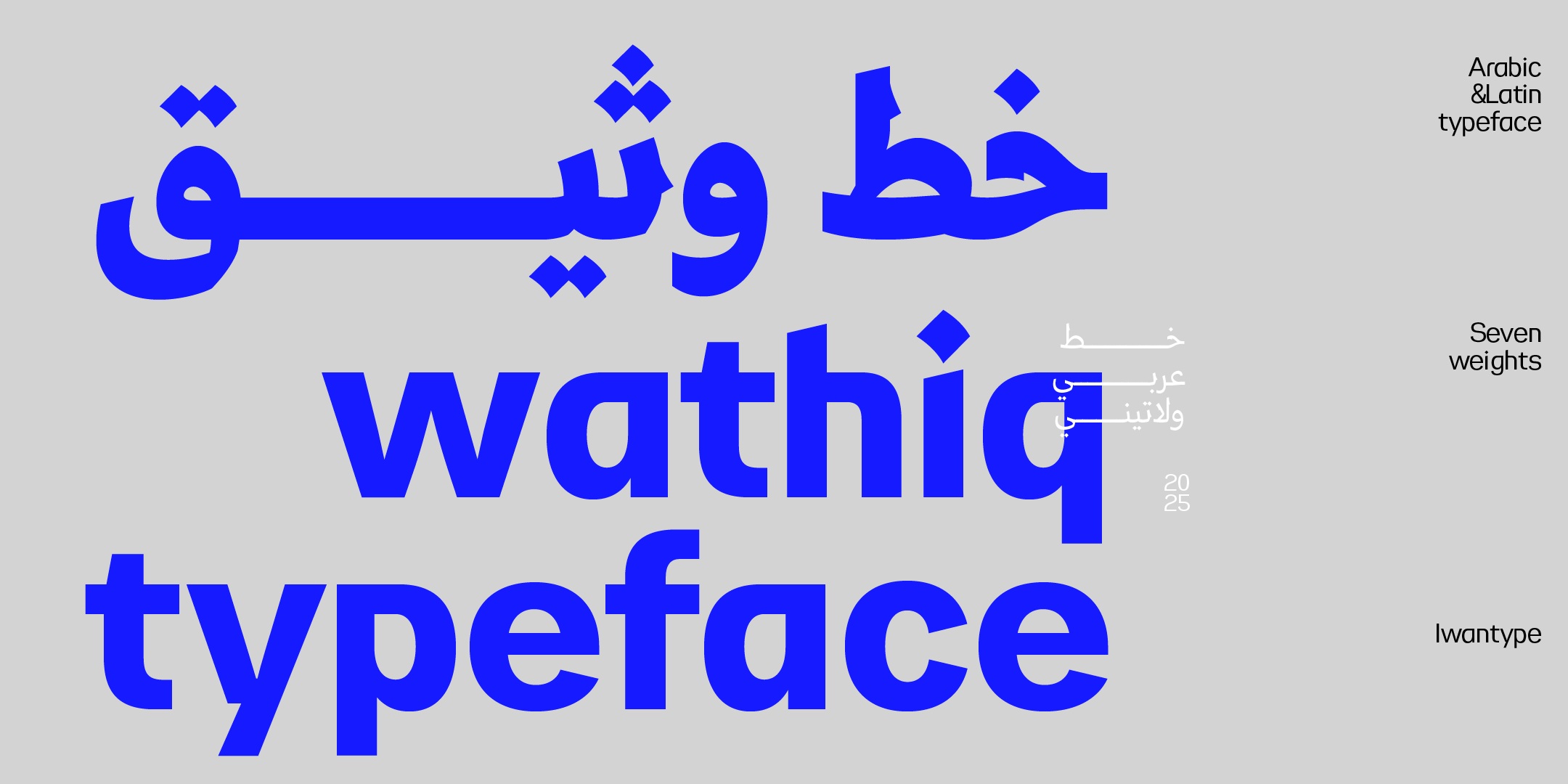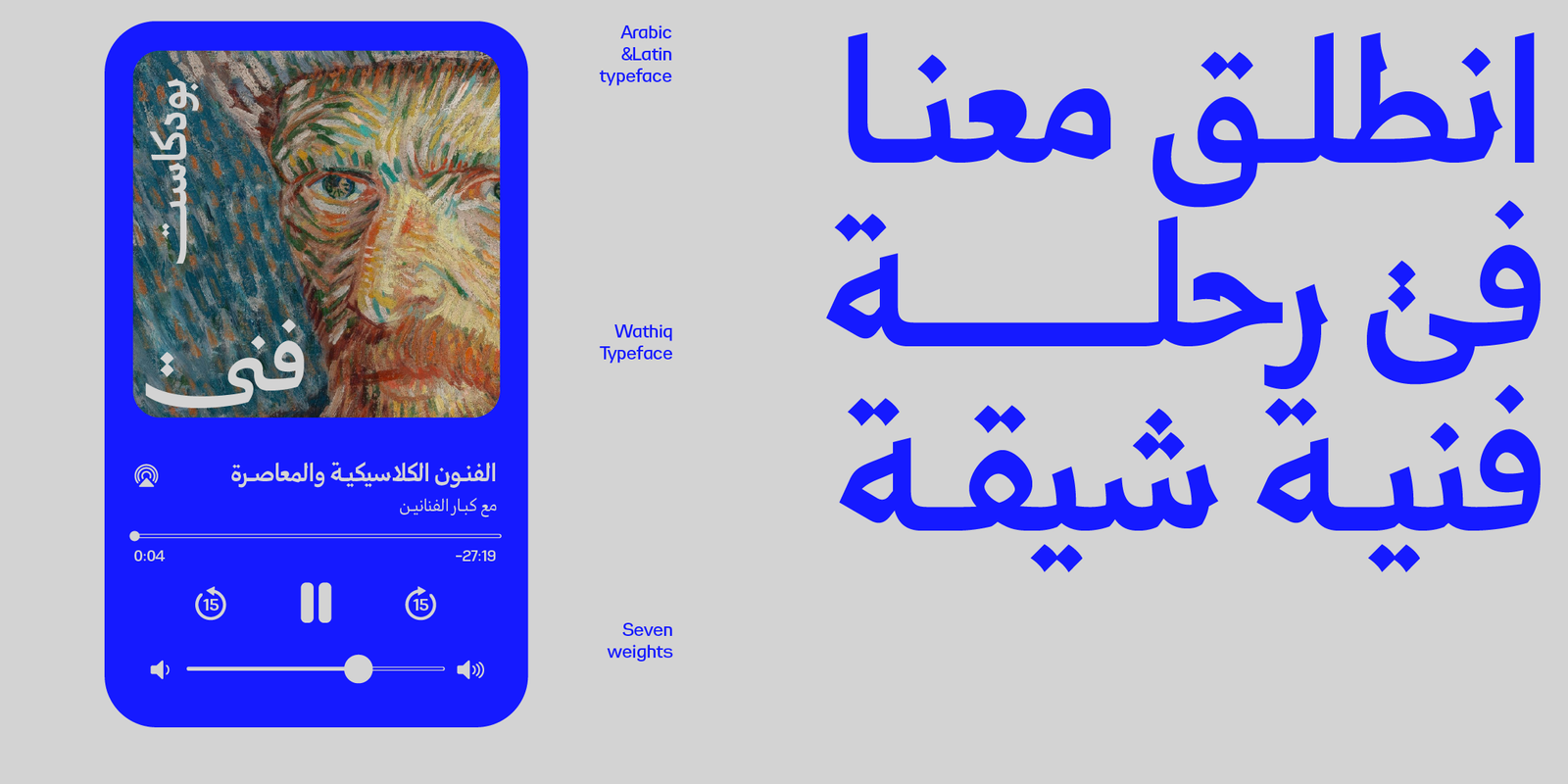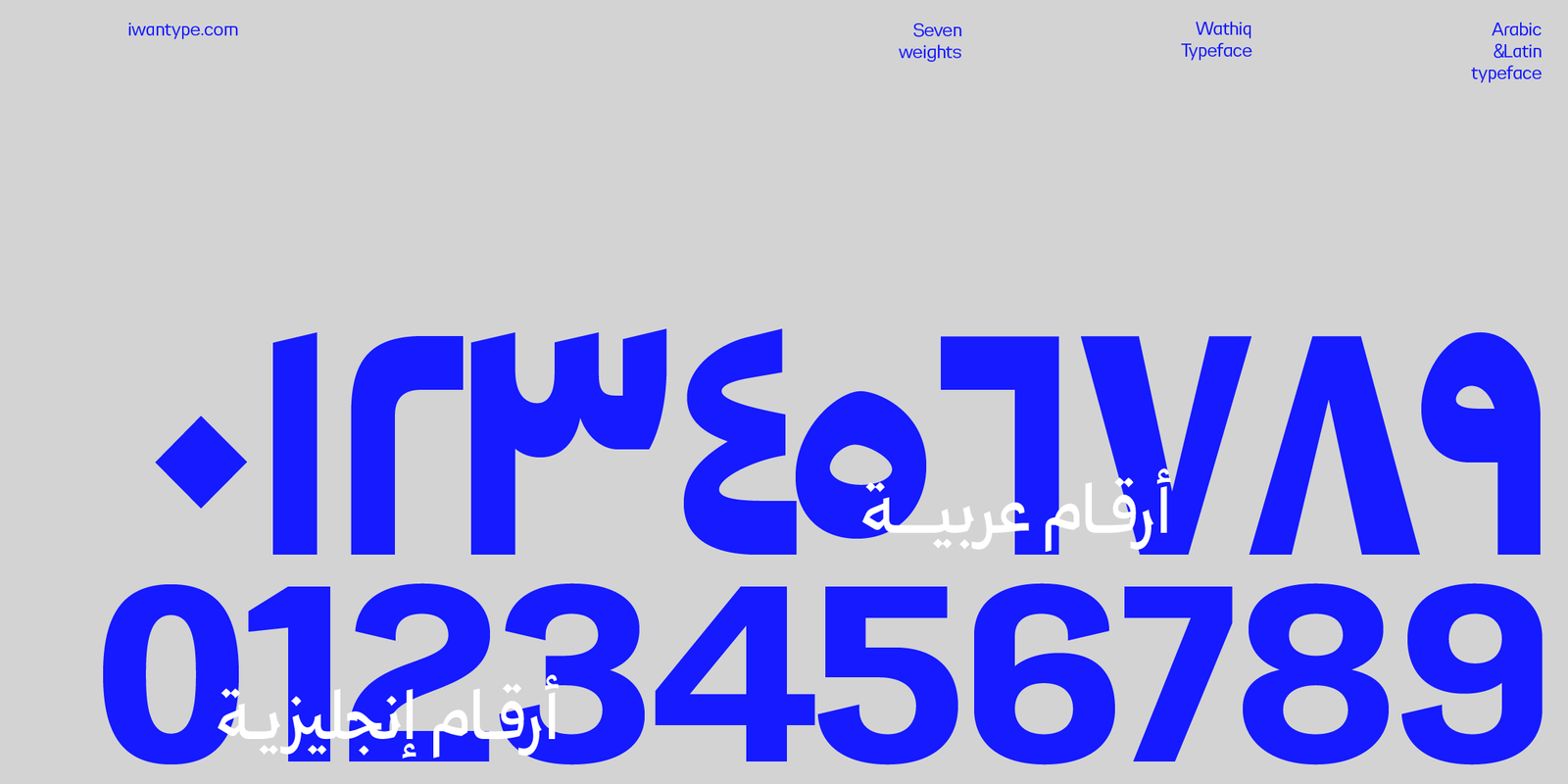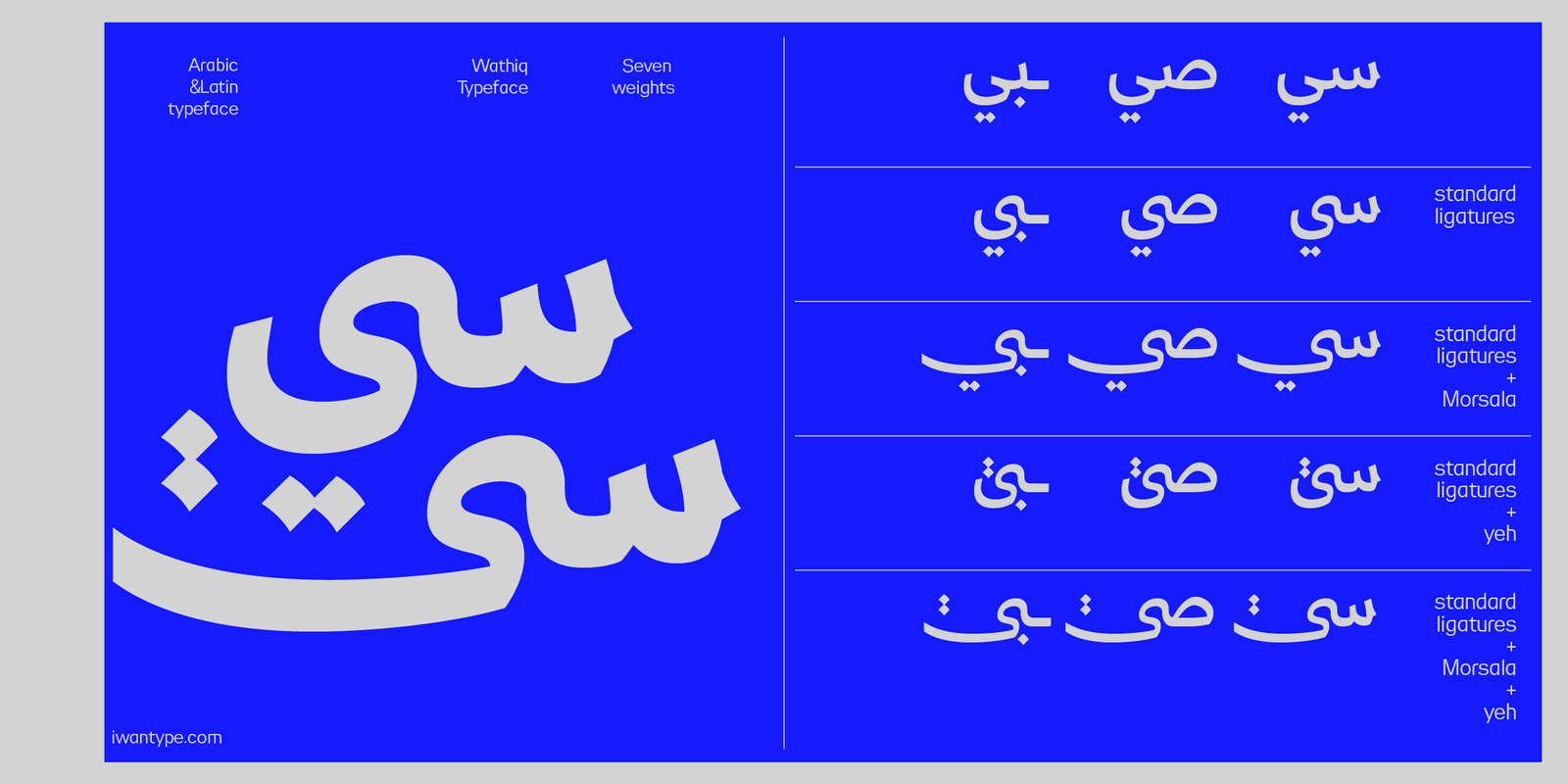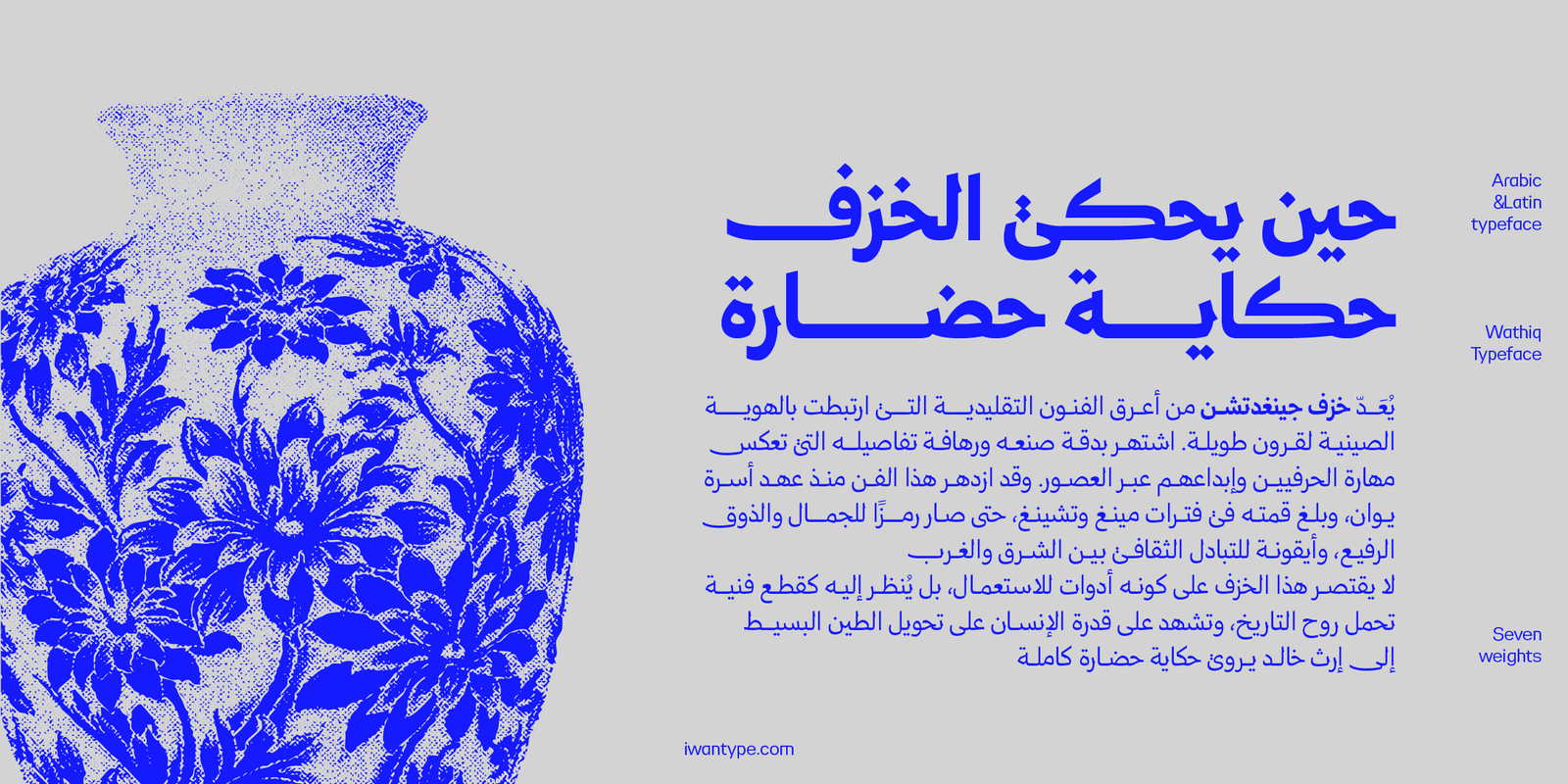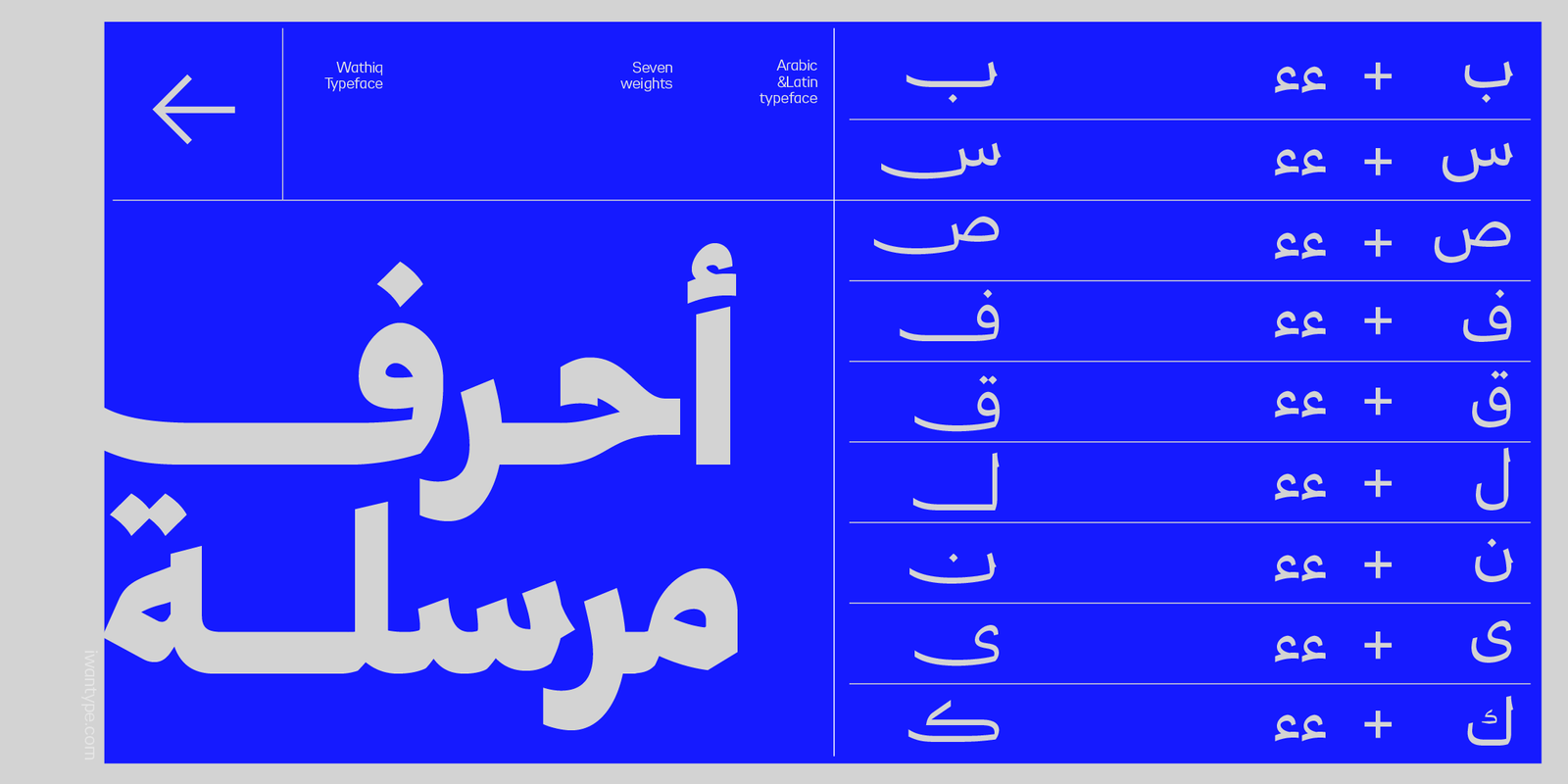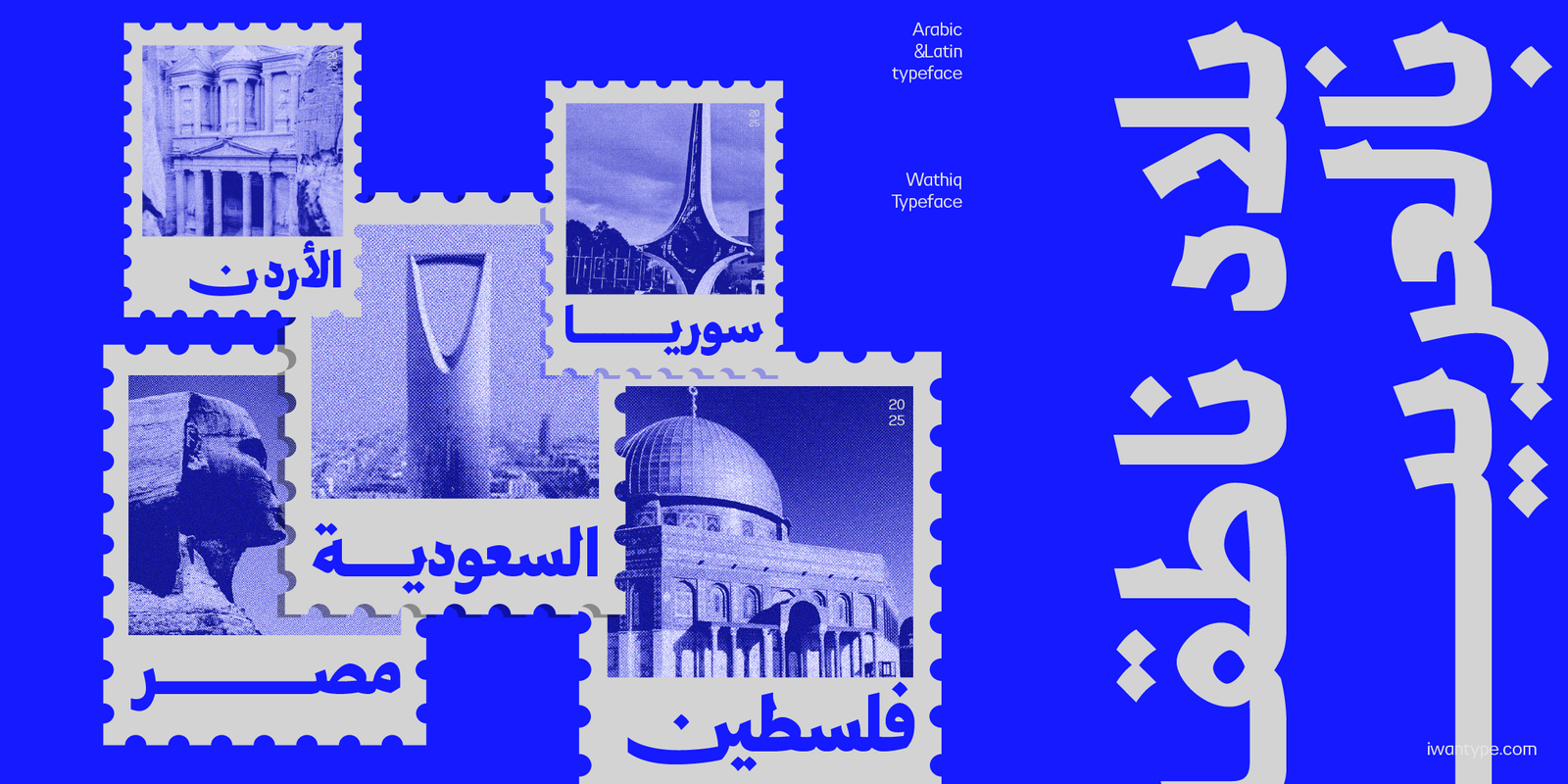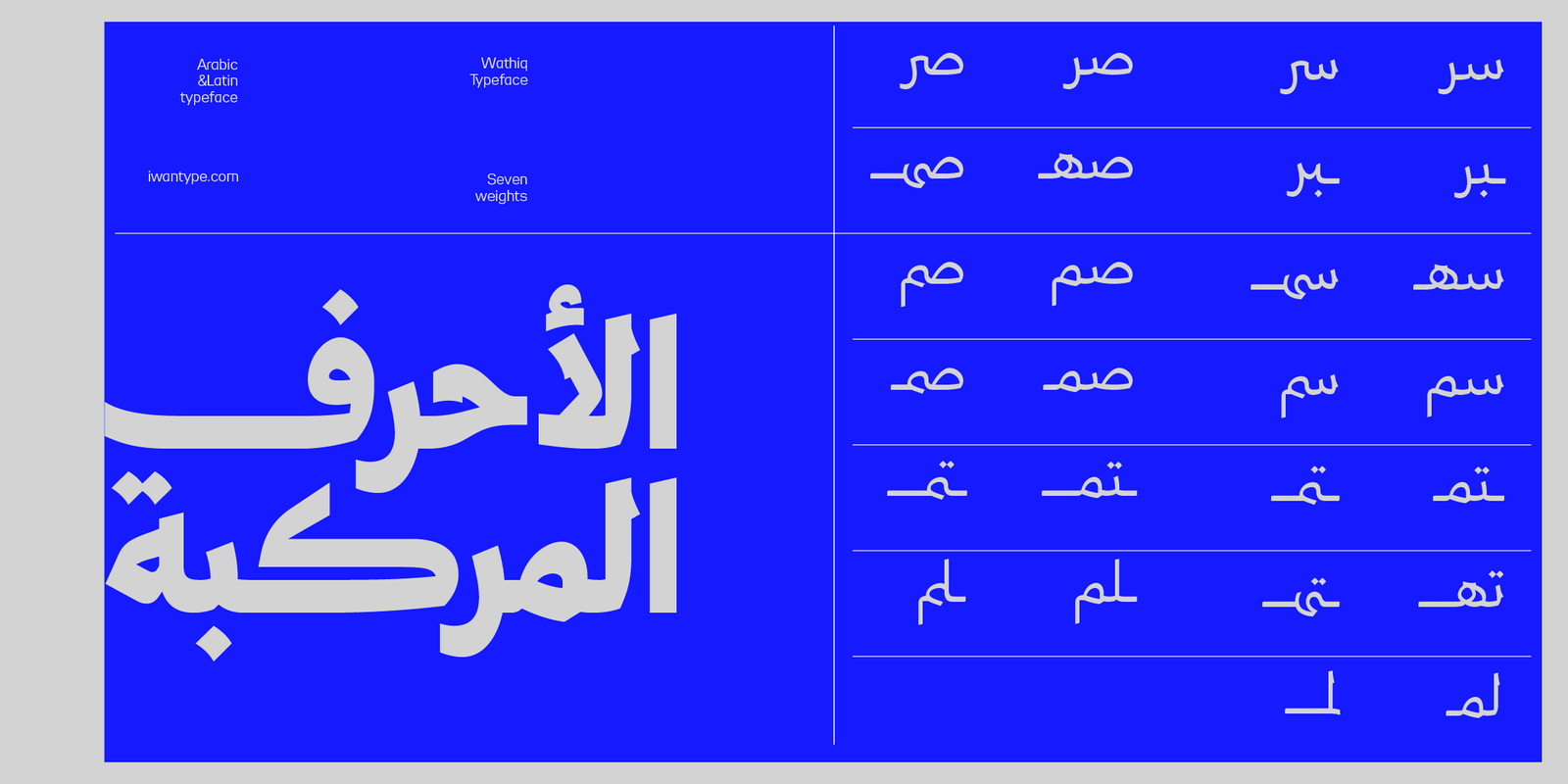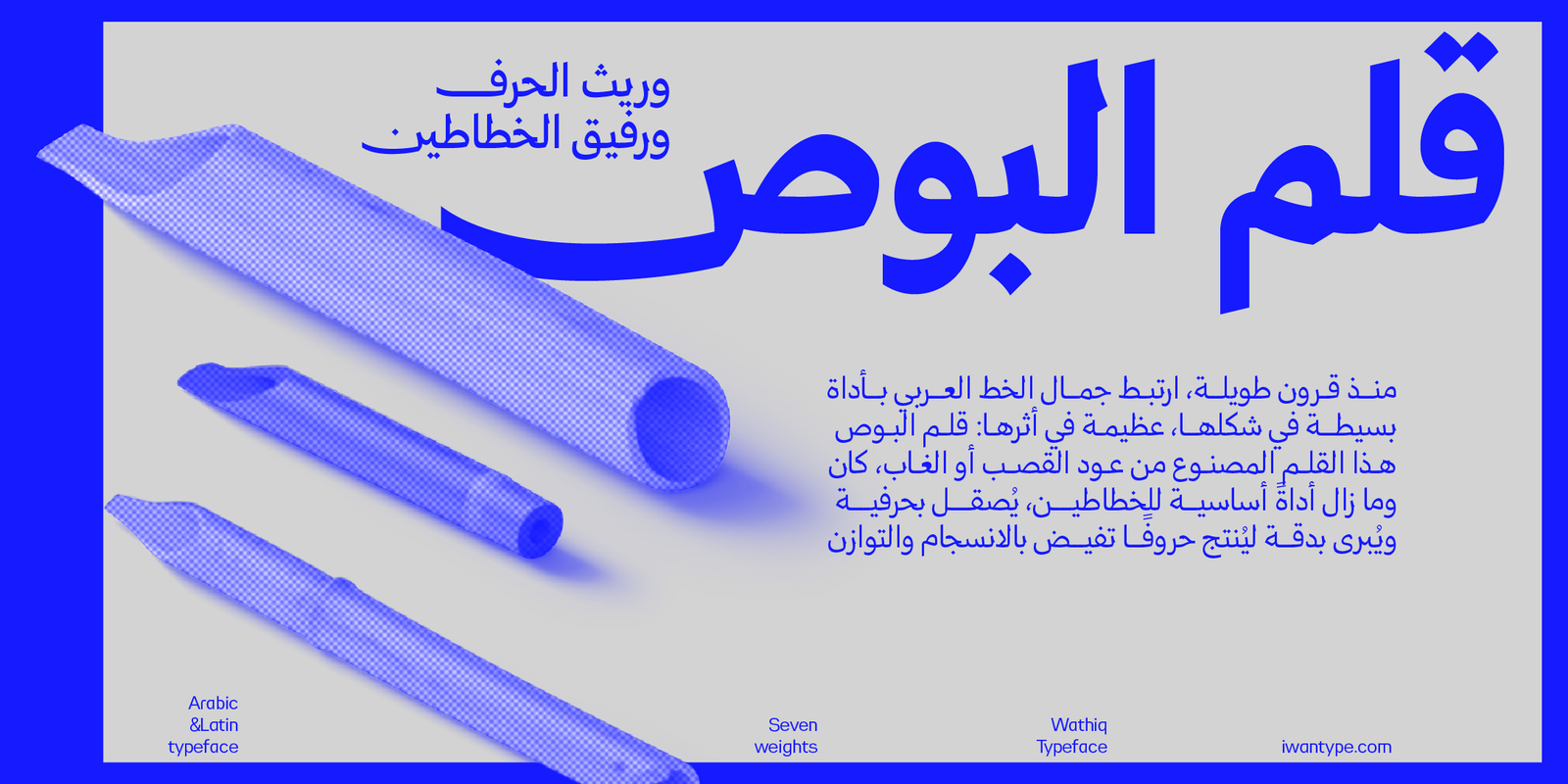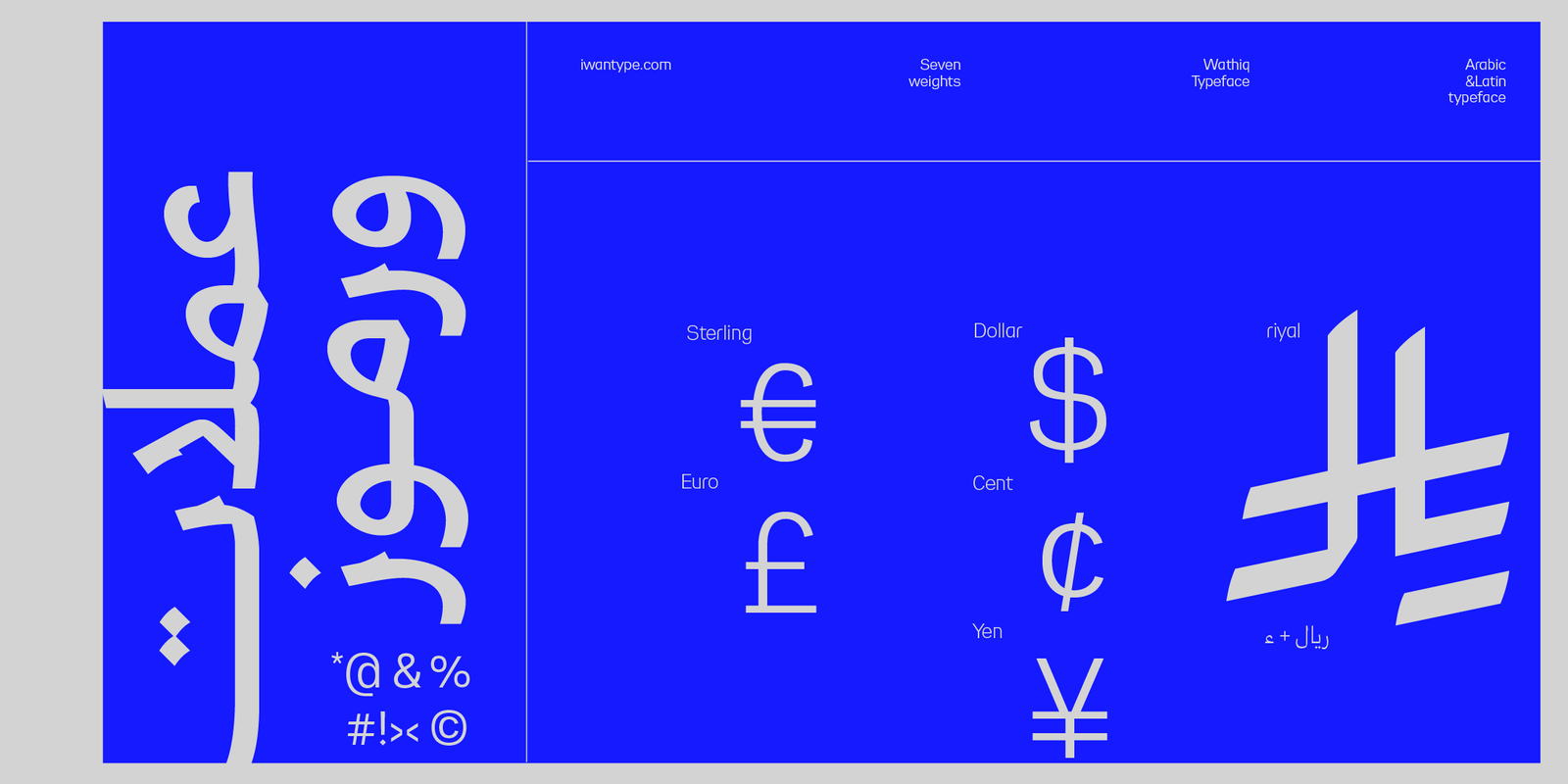
خط وثيق Wathiq Typeface – خط نسخ حديث
خط وثيق Wathiq Typeface – خط عربي ولاتيني حديث مستوحى من النسخ والثلث، مثالي للعناوين والأخبار والشعارات، متوفر بسبعة أوزان Modern Arabic & Latin Font (7 Weights).
خط وثيق هو خط عربي–لاتيني حديث يجمع بين أصالة خط النسخ وجماليات من الثلث بلمسة معاصرة. يتميز بحروف واضحة، حواف قوية، وتجويفات داخلية ضيقة تمنحه شخصية متينة ومناسبة للاستخدامات الرسمية والإعلامية.
يأتي خط وثيق بسبعة أوزان متدرجة من Light حتى Black، مما يجعله مثاليًا لمجموعة واسعة من التطبيقات مثل:
العناوين الصحفية والإخبارية
البودكاست والهوية السمعية البصرية
الشعارات والهوية المؤسسية
التصميم الطباعي والإعلانات
بفضل توافقه الكامل مع اللغتين العربية واللاتينية، يقدم وثيق تجربة متوازنة للمصممين العاملين في مشاريع ثنائية اللغة، ليصبح خيارًا موثوقًا لكل من يبحث عن خط عربي معاصر، قوي وواضح.
مميزات خط وثيق:
يتضمن الخط العديد من مزايا OpenType التي تضفي عليه مرونة وتنوعًا في الاستخدام، مثل:
- أحرف مرسلة (تُفعَّل بإضافة “ءء” بعد الحرف)
- حرف ياء بنزول أقل: يقلل من نزول السطر، مما يعزز من انتظام النصوص.
- أحرف المركبة: تسهم في تحسين المظهر العام للنص وتزيد من سلاسته.
- نقاط بديلة
- يدعم رمز الريال السعودي، ويمكن تفعيله بإضافة حرف “ء” بعد كتابة كلمة “ريال”.